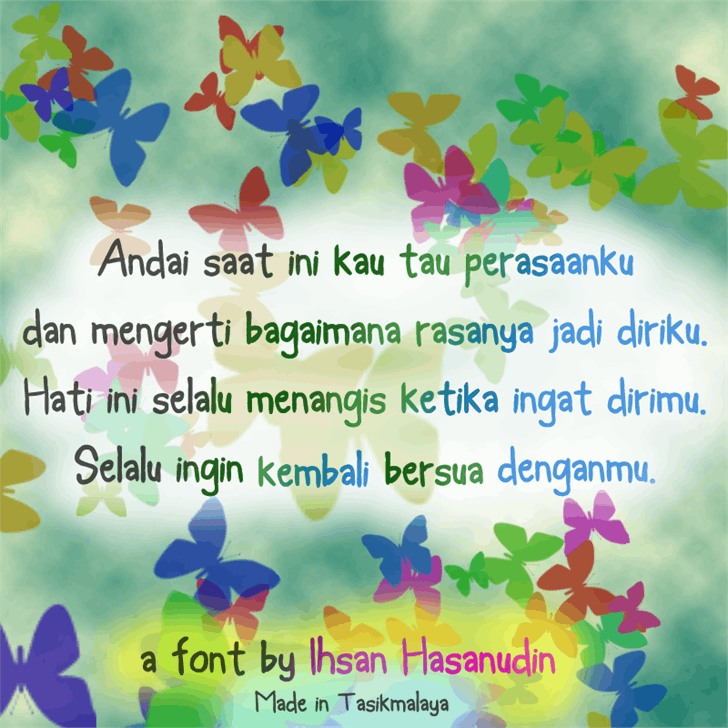
A fonte ‘Blee Guys’ é uma curiosa escolha para aqueles que buscam algo único e divertido no seu próximo projeto. Inspirada nos traços manuscritos, esta fonte foi criada pelo designer Hamilton, e seu estilo surpreendentemente reúne um conjunto de nomes de designers ilustres do Indonesia – todos com uma ligação direta a quem inspirou este design, incluindo Acep Muhamad Anwar, Blecep Firman Nugraha, Emon Dede Mulyana, Emul Debi Fauzi Rohendi e Ebing Win Berkat Nurdianto. A fonte é particularmente bem adaptada para aplicações que exigem um toque de personalização ou criatividade, como logotipos, artes digitais, arte digital, criação de material editorial, design gráfico, design de mídia social e outras plataformas visuais. Com sua aparência autêntica e singular, ‘Blee Guys’ se destaca entre as fontes manuscritais do mercado atual, prometendo oferecer uma combinação única de estilo único e facilidade de uso. É perfeito para quem busca personalização sem sair da estrada, trazendo um toque autêntico às suas criações digitais.